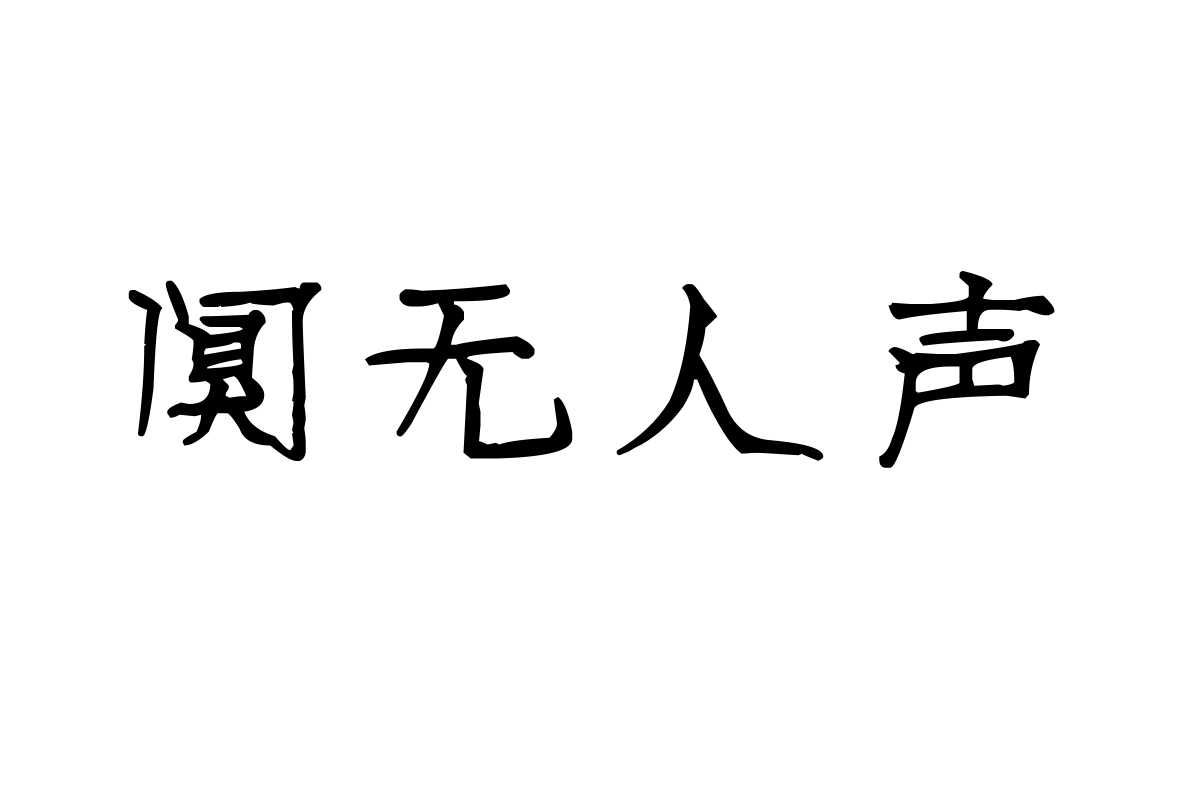
蝉羽刀剑笑是一种中文字体,由汉仪字库设计。这款字体以其独特的风格和特点而受到许多设计师和艺术家的喜爱。它采用了传统的书法元素,结合了现代的设计理念,创造出一种既有古典韵味又不失现代感的字体。
蝉羽刀剑笑的特点包括:
1. 字形优美:这款字体的字形线条流畅,结构紧凑,给人一种优雅的感觉。
2. 笔画丰富:蝉羽刀剑笑的笔画丰富多样,既有直线也有曲线,既有粗线也有细线,给人一种丰富的视觉体验。
3. 风格独特:这款字体的设计灵感来源于古代的书法艺术,因此它具有浓厚的传统文化气息。
4. 适用广泛:蝉羽刀剑笑适用于各种印刷品、广告、包装等场合,具有很强的实用性。
总的来说,蝉羽刀剑笑是一款非常优秀的中文字体,它的出现为设计师们提供了更多的选择,也使得更多的人能够欣赏到这种独特的字体风格。